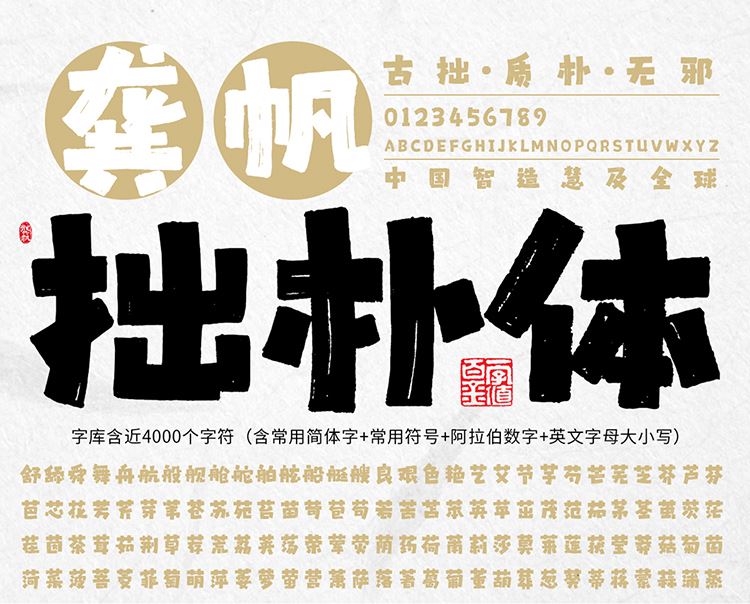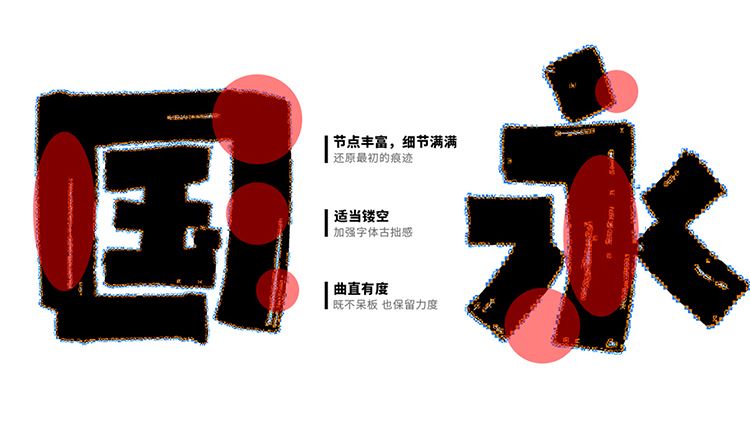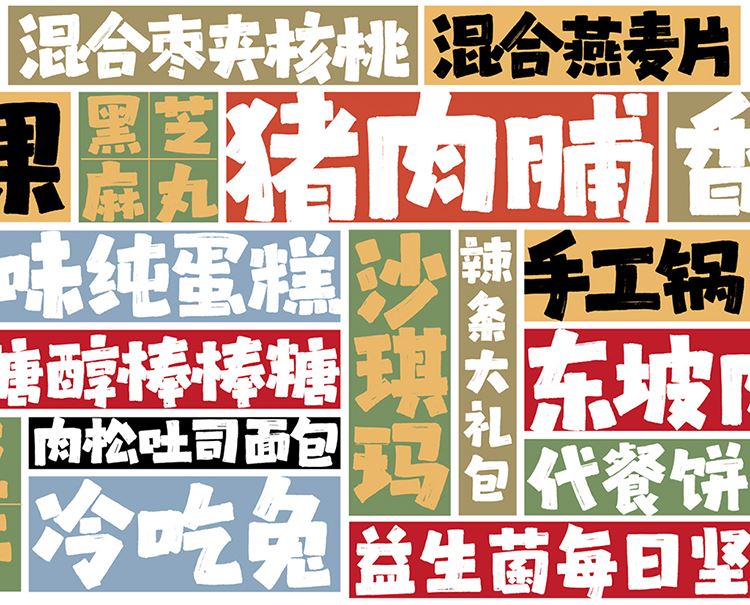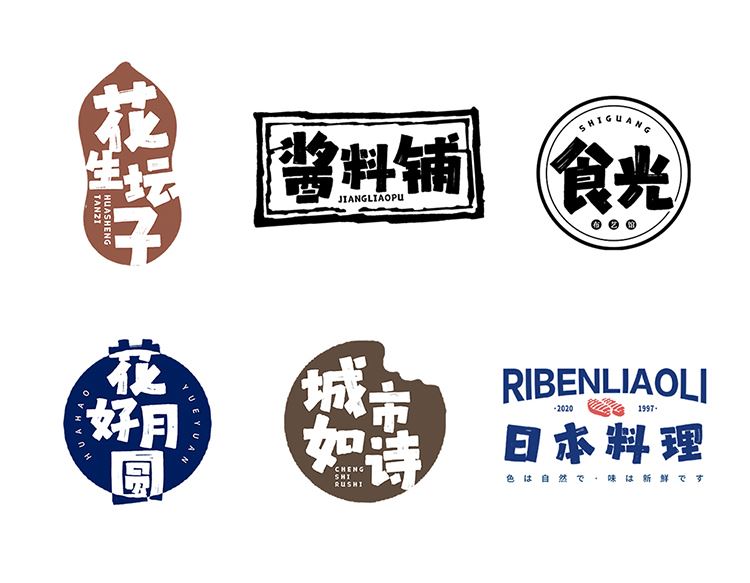
龔帆拙樸體是一款具有古拙·質(zhì)樸·無邪等特征的藝術(shù)字體,字體節(jié)點豐富,細(xì)節(jié)慢慢,還原最初的痕跡;適當(dāng)鏤空 ,加強(qiáng)字體的古拙感;曲直有度,既不呆板,也保留力度。龔帆拙樸體字庫含近4000個字符(含常用簡體字+常用字符+阿拉伯?dāng)?shù)字+英文字母大小寫),適用于包裝設(shè)計、電商、品牌名稱、漫畫、影視綜藝、游戲、各類商業(yè)海報、戶外廣告標(biāo)題等設(shè)計領(lǐng)域。歡迎喜歡此字體的朋友前來下載使用。